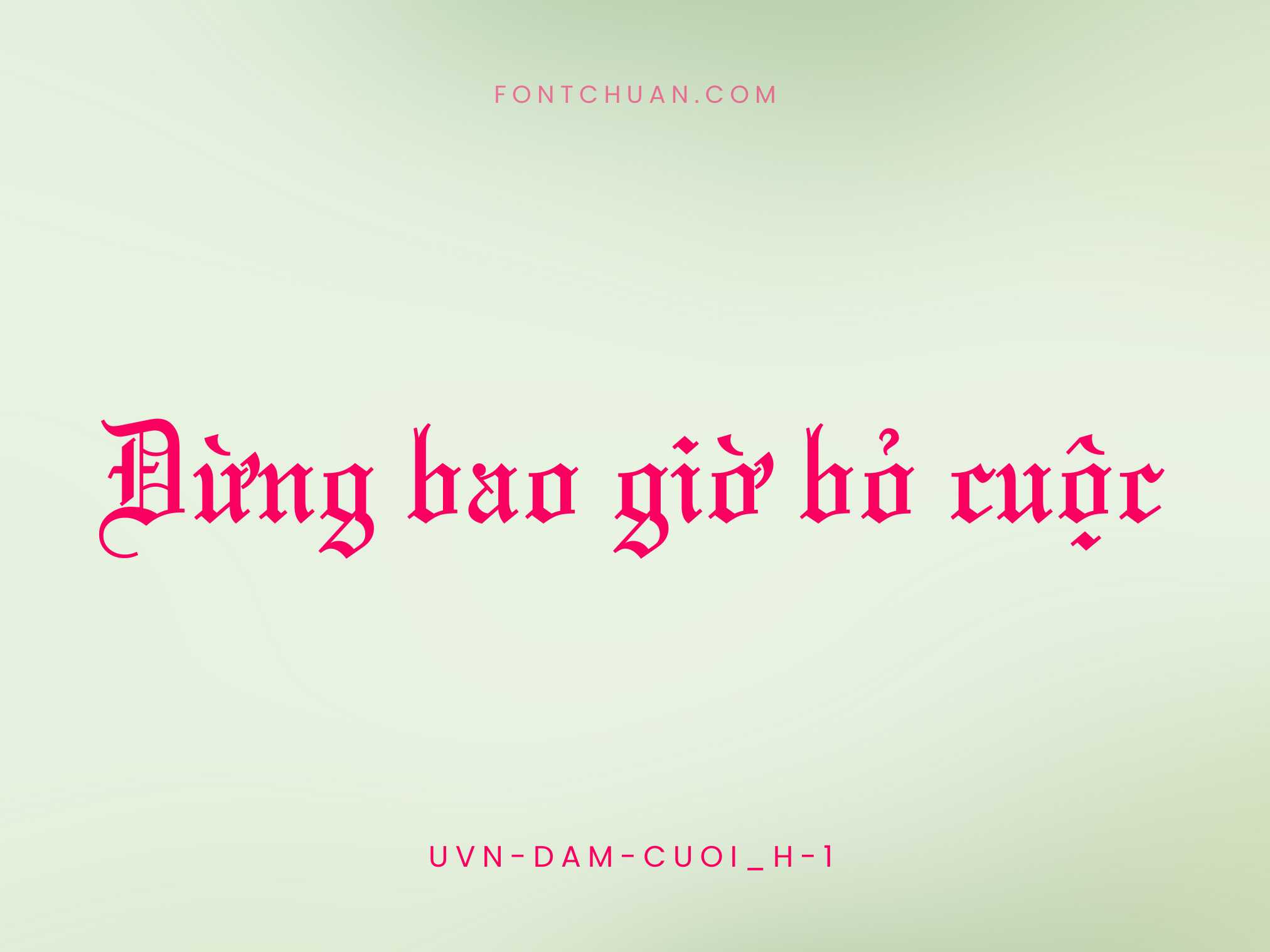
Font UVN Dam Cuoi Hep Việt Hóa
UVN Đám Cưới Hẹp là một phông chữ blackletter mang phong cách cổ điển với các chi tiết phức tạp, lấy cảm hứng từ nghệ thuật gothic. Phông chữ này có các nét chữ sắc nét, góc cạnh và trang trí tinh xảo, tạo nên vẻ ngoài lịch sử và trang trọng. UVN Đám Cưới Hẹp hỗ trợ đầy đủ các ký tự tiếng Việt, giúp người dùng dễ dàng sử dụng trong các dự án sáng tạo liên quan đến văn hóa Việt Nam.
Với thiết kế độc đáo và nghệ thuật, UVN Đám Cưới Hẹp phù hợp cho các ứng dụng như thiệp mời, tiêu đề sách, thiết kế logo và các ấn phẩm nghệ thuật. Trong lĩnh vực sự kiện, phông chữ này có thể được sử dụng trong các dịp như lễ hội, lễ cưới và các sự kiện văn hóa. Ngoài ra, UVN Đám Cưới Hẹp còn là một Font chữ ảnh cưới lý tưởng, mang đến sự trang nhã và tinh tế cho các album cưới, thiệp cưới và các sản phẩm lưu niệm đặc biệt. Font này cũng thích hợp cho các ngành nghề như thiết kế đồ họa, nghệ thuật trang trí và xuất bản.